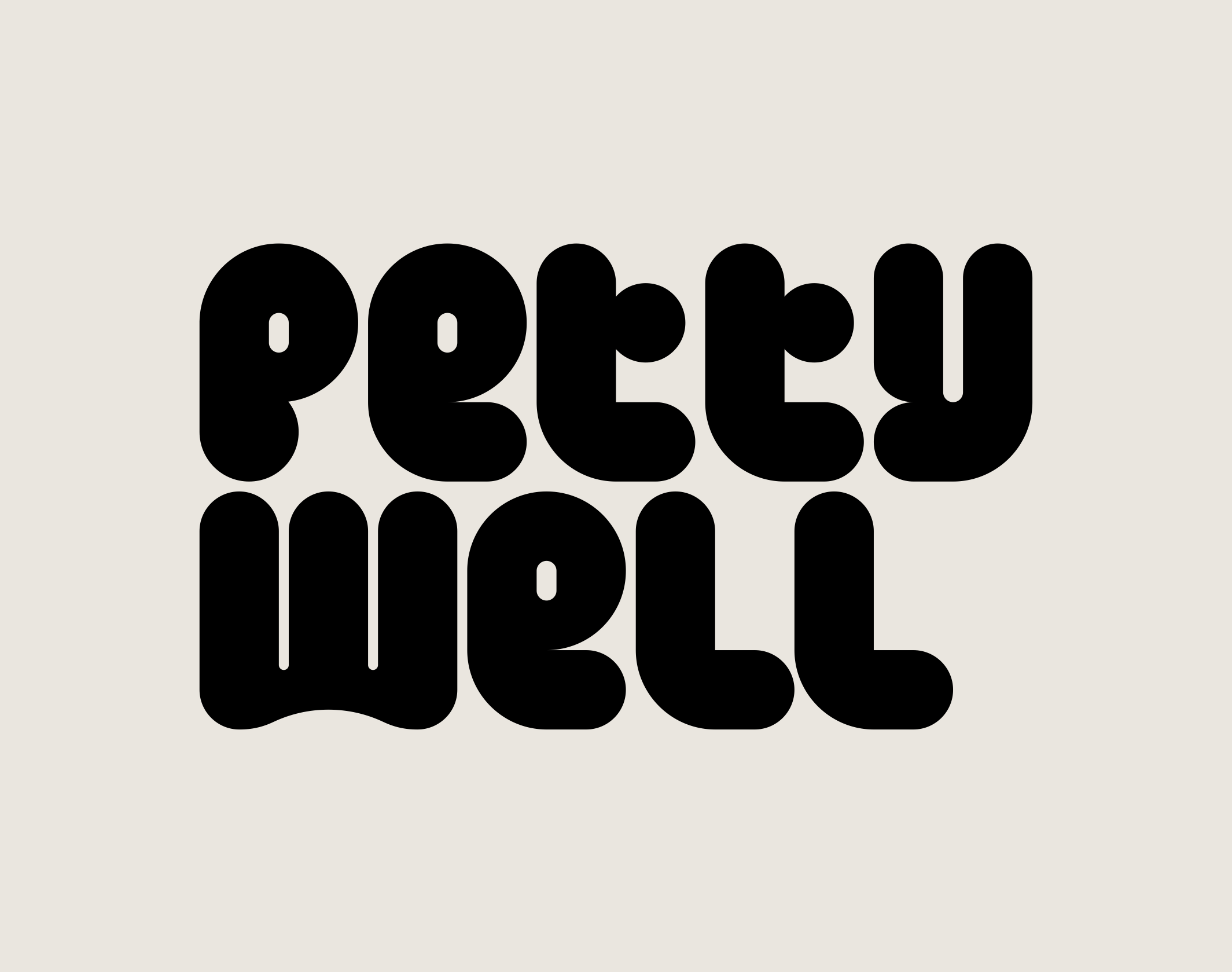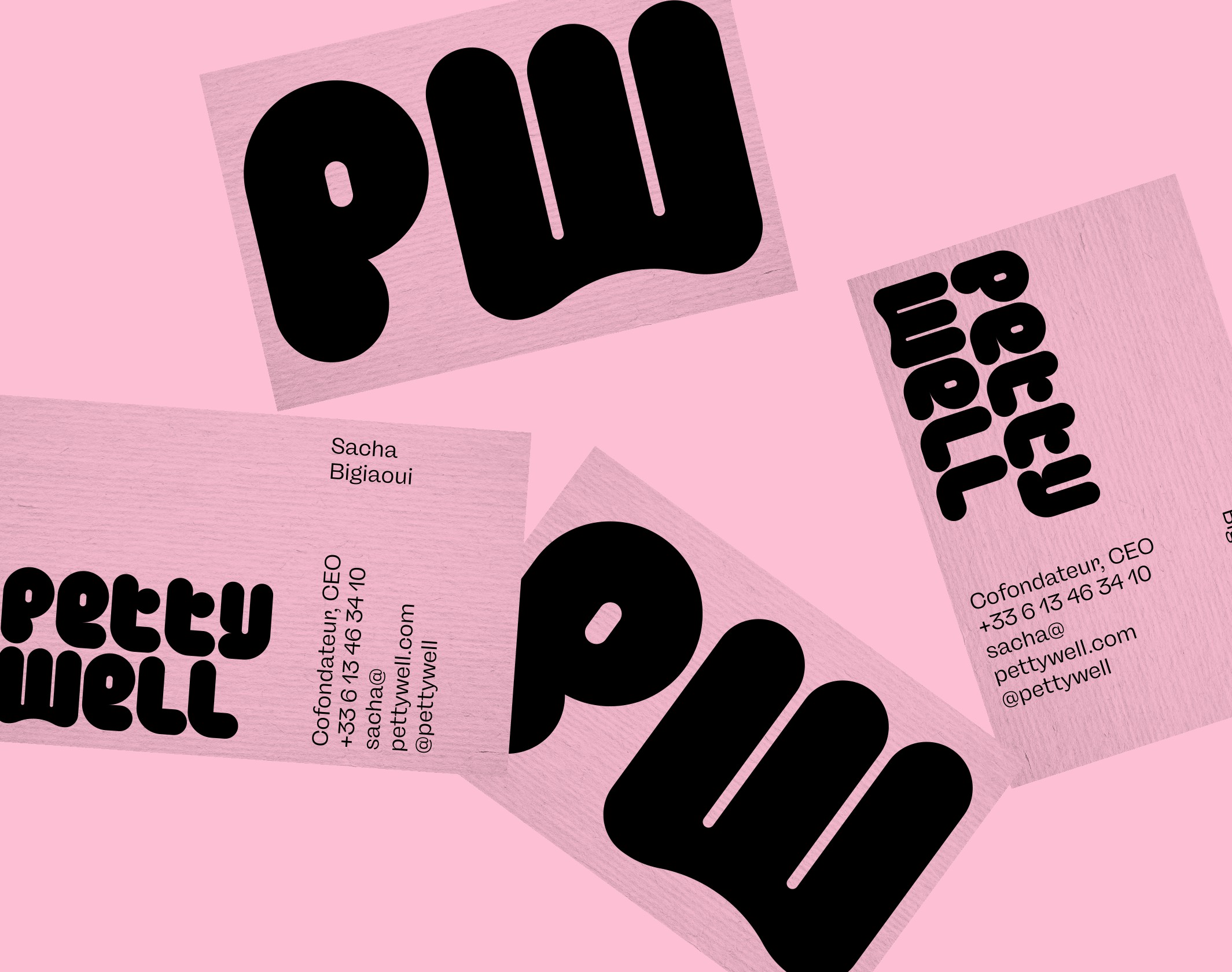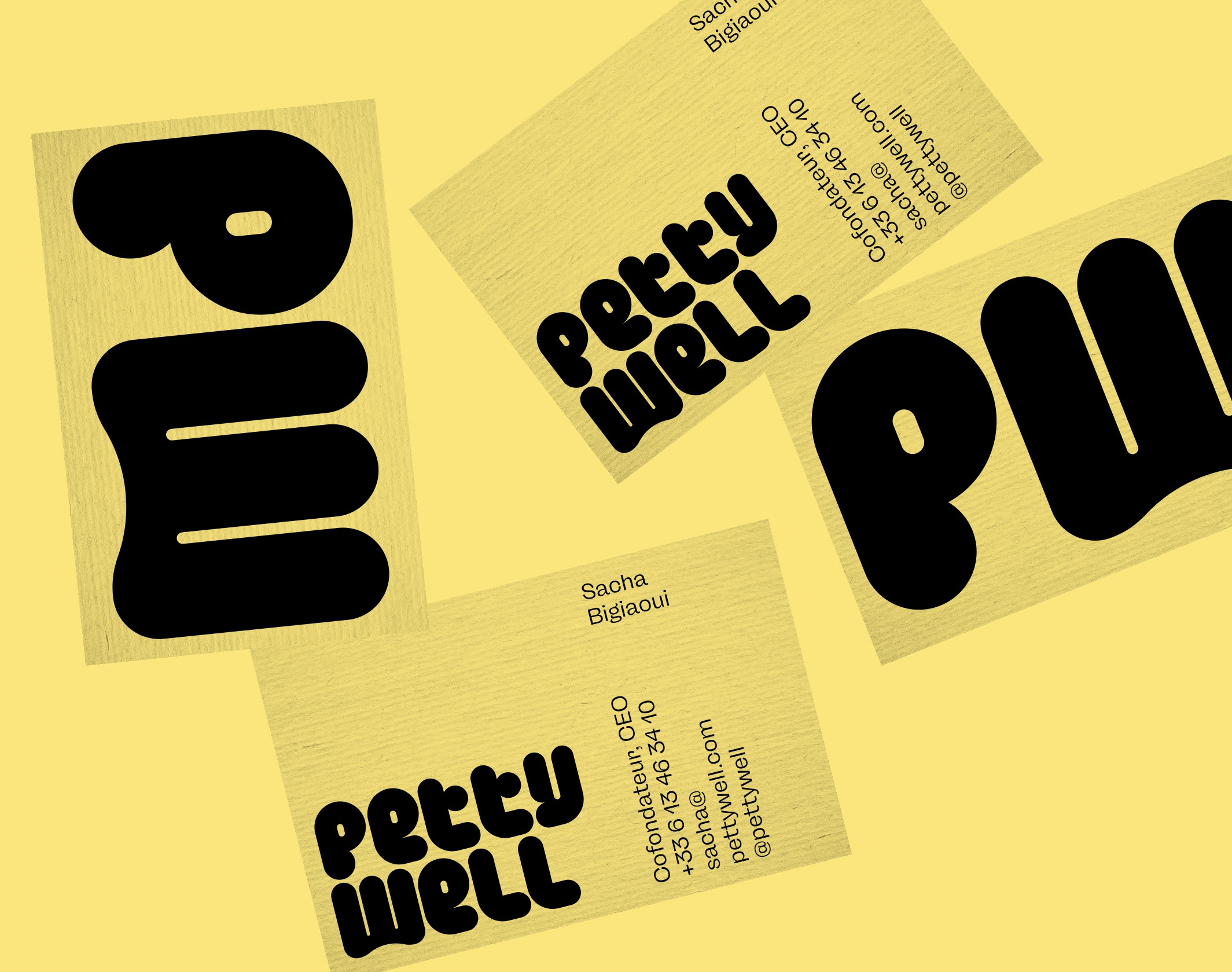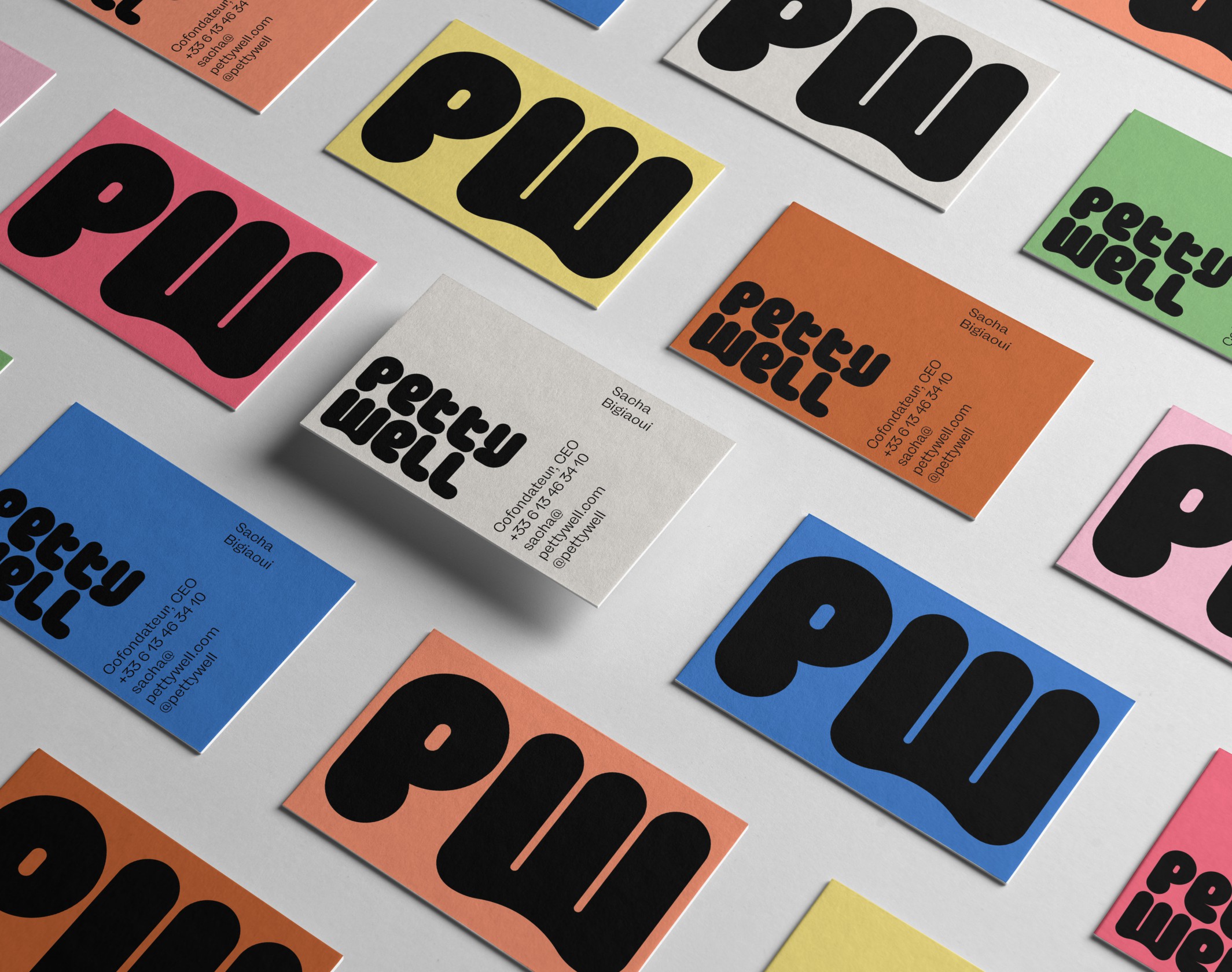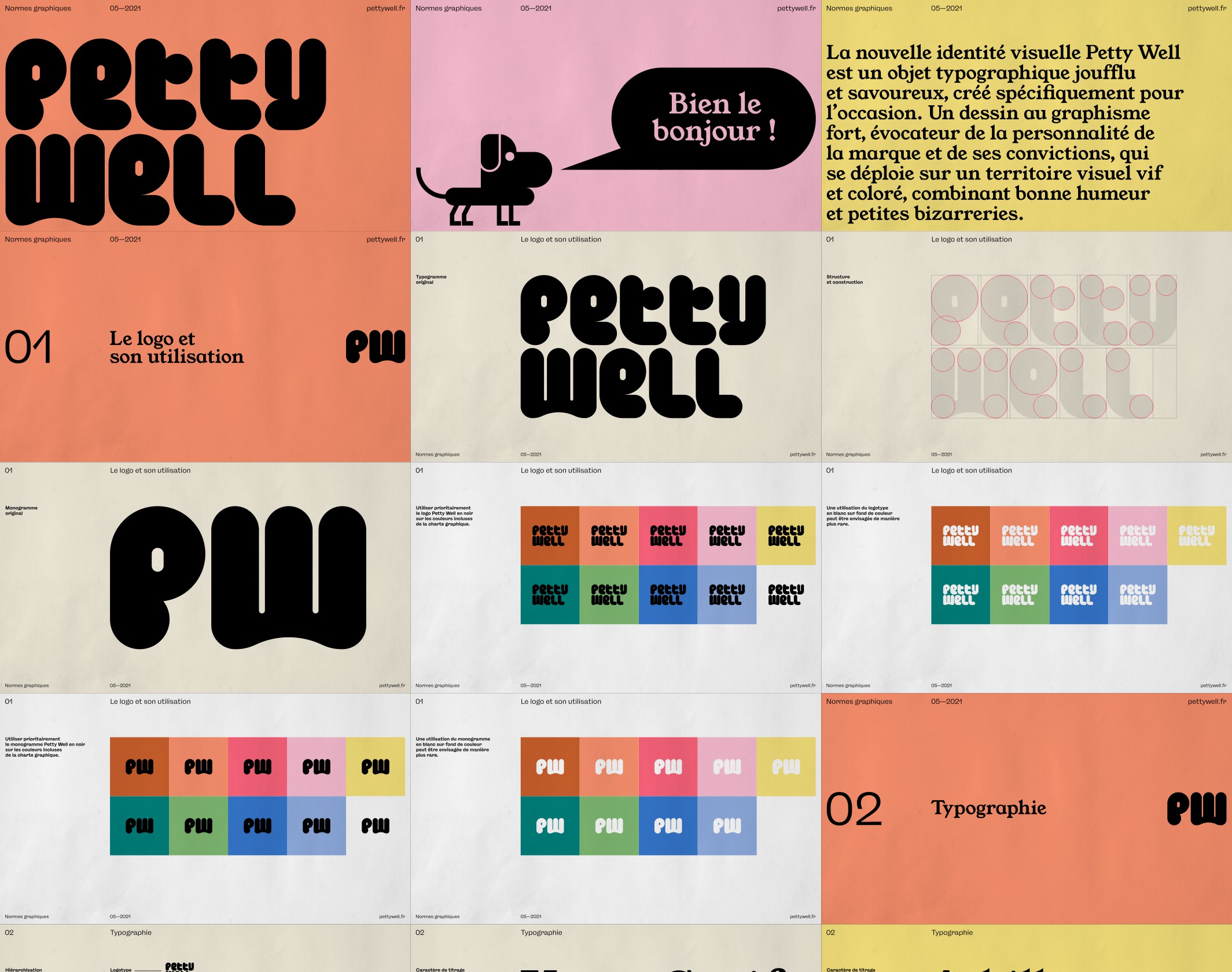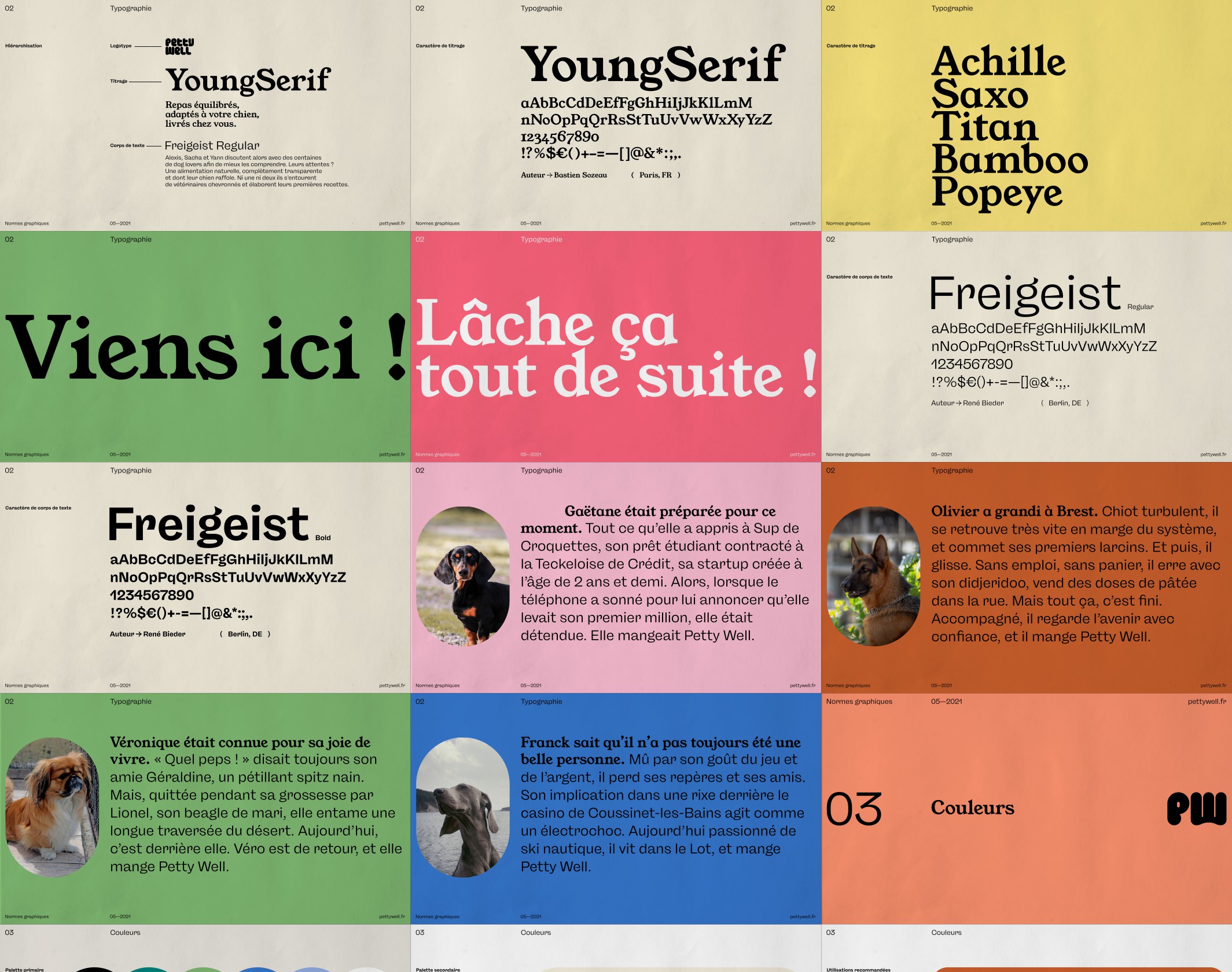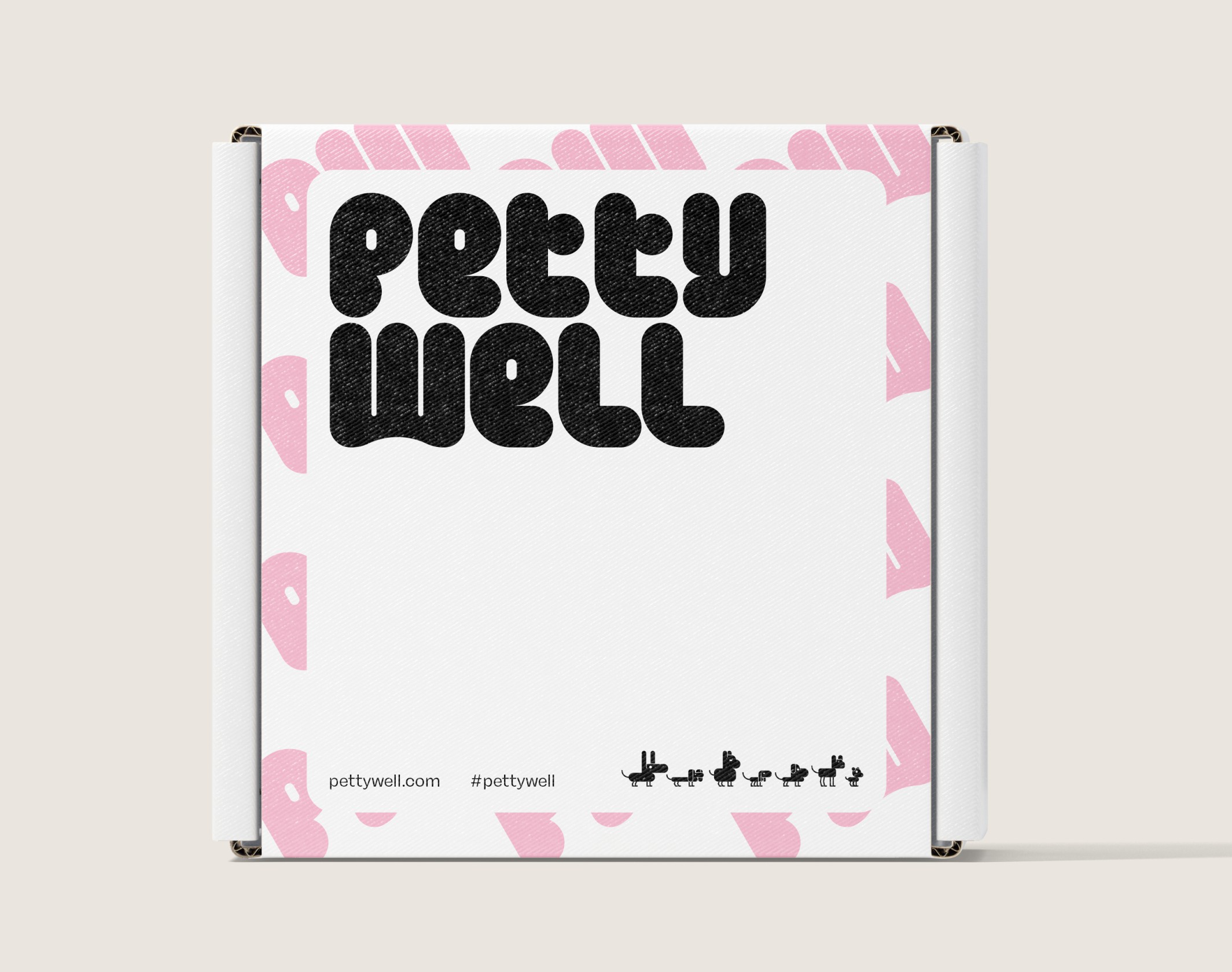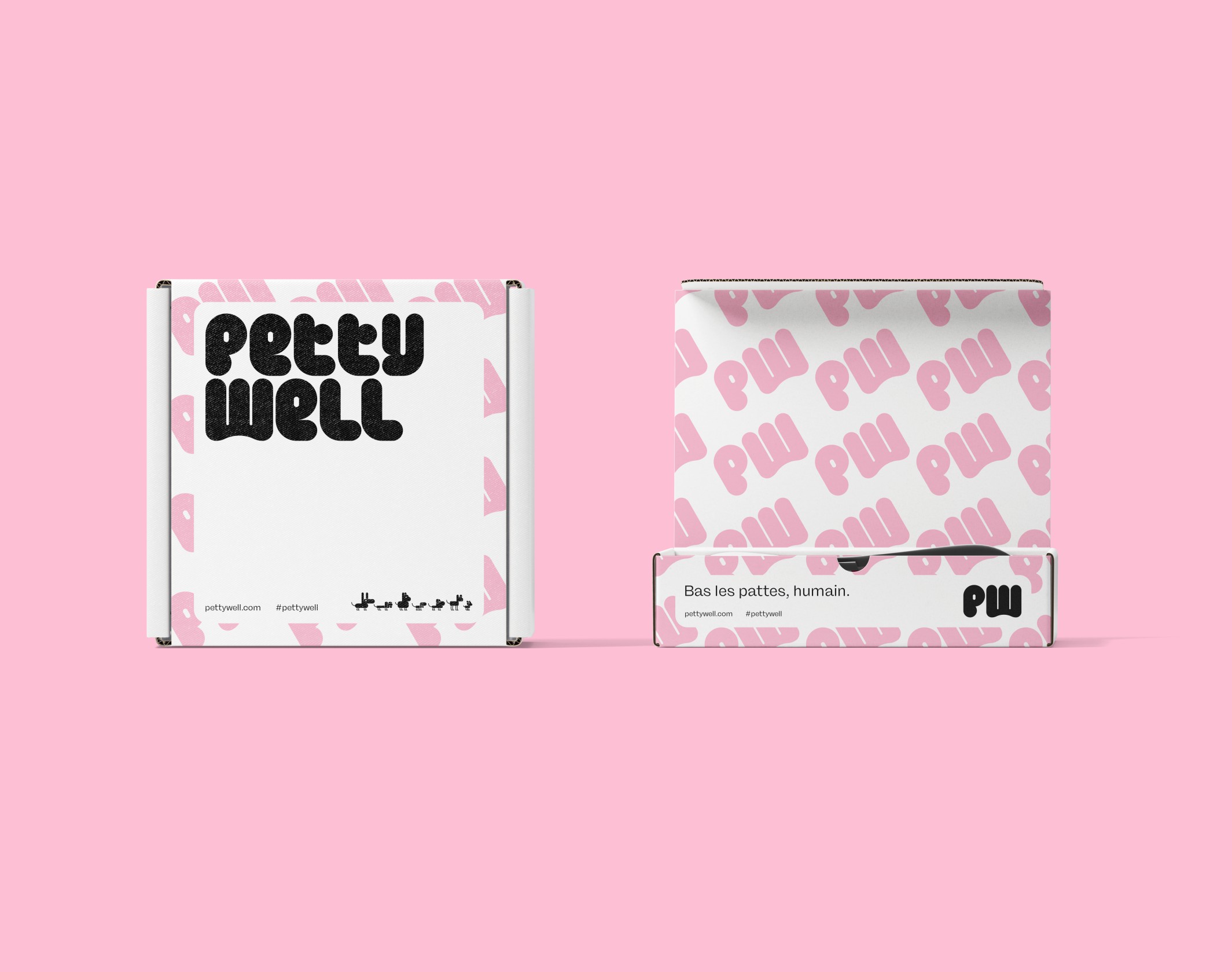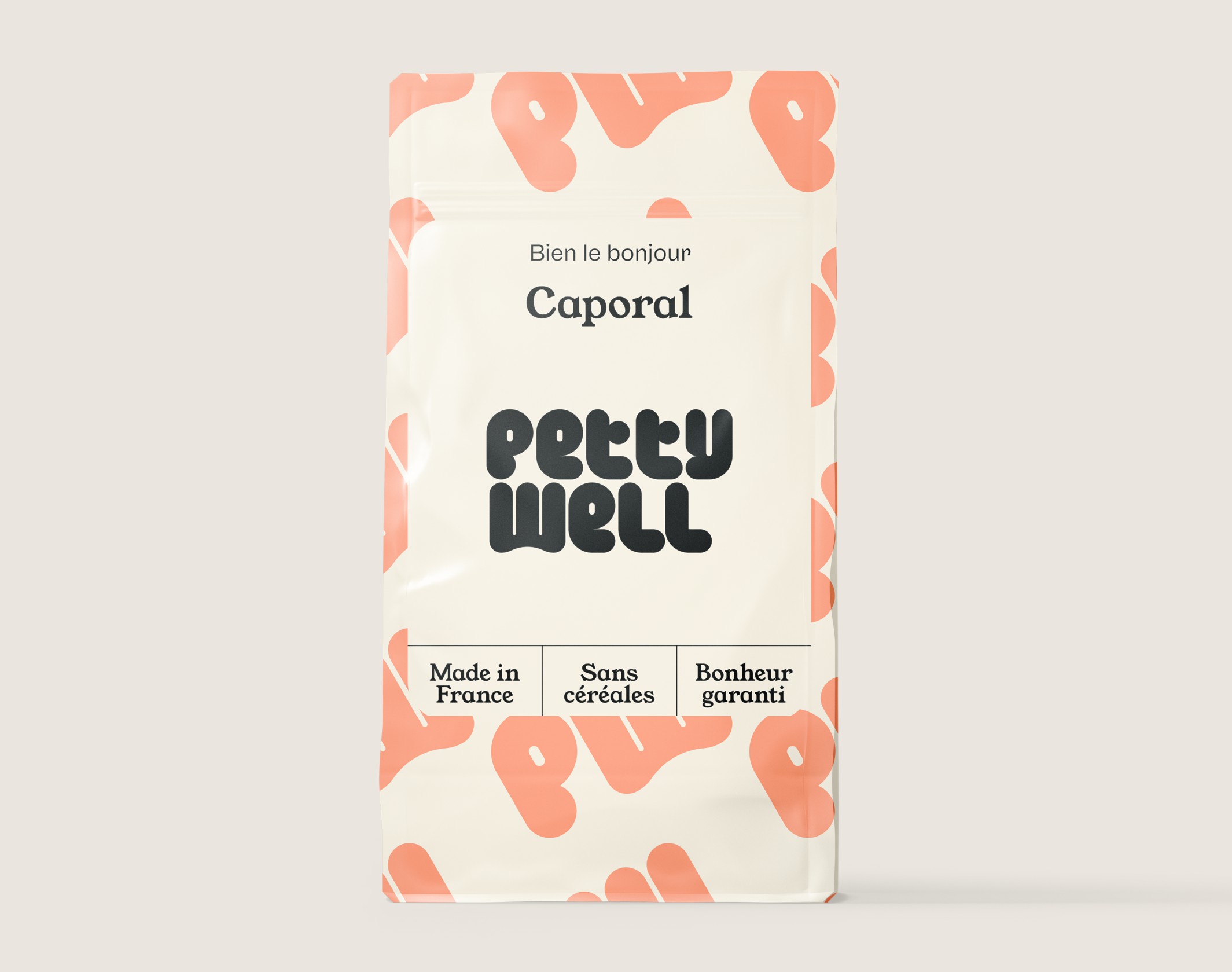
Petty Well
Petty Well, acteur majeur de l'alimentation saine pour animaux, se réinvente avec une identité visuelle colorée et graphique pour séduire sa communauté grandissante
Petty Well est un des acteurs français les plus importants de la nourriture saine pour chiens et chats. Créée par Sacha et Alexis, la marque propose des croquettes et pâtées naturelles, produites en France et adaptées à chaque animal, sous forme d’abonnement. Après quelques années de lancement et un véritable succès, une communauté de plus de 4000 clients s’est formée autour de Petty Well, et notre studio a été chargé d’en redéfinir l’identité visuelle.
Le nouveau logo est un dessin typographique original, joufflu et savoureux mais empreint d’une structure fort et régulière. Il représente l’ossature du territoire visuel ; ce dernier se veut vif et coloré, tout en restant brut et graphique en maintenant une présence constante du noir et de fonds monochromatiques. Nous avons développé une collection d’animaux basés sur le graphisme du logotype, qui vivent et s’animent sur les différents supports de la marque ; print, packaging et web. Le lancement de la nouvelle identité a eu lieu au printemps 2021 et comportera plusieurs étapes successives jusqu’à la finalisation complète du déploiement.